Display
Das eng. Lehnwort »Display« hat in der dspr. Typografie sehr unterschiedliche Bedeutungen. Es wird sowohl für Werbemittel (z.B. Verkaufsplakat am Point of Sale), für Bildschirme (z.B. LED-Display eines Kopierers), für bestimmte Schriftgrade einer Druckschrift (Displaygröße), für eine »Optische Größe« (Optical Sizes) einer Schriftfamilie einer Screen- oder Druckschrift sowie für stilübergreifende Akzidenz- und Zierschriften (Display Typefaces) verwendet.
Etymologisch rührt das Wort von eng. »Display« für »Entfaltung, (Her)Zeigen, Zurschaustellung« (von lat. »displicare für »entfalten«) zu »Auslage, Dekoration« im Sinne von »Ausstellung von Waren im Schaufenster«. Der Begriff Display wurde in Deutschland erstmals in den 1950er Jahren von Werbeagenturen für verkaufsfördernde Werbemittel am »Point of Sale« (z.B. Plakate, Bodendisplays, Thekendisplays oder 3D-Verkaufsdisplays am Ort des Verkaufes) verwendet und folgend in die gängige Werbesprache integriert.
Mit der Etablierung der »Werbung« als Dienstleistung nach US-amerikanischem Vorbild und mit Einführung der dritten Generation von Fotosetzmaschinen (siehe Fotosatz) ab Ende der 1960er Jahre, wurde die Bezeichnung dann auch von den Fotosetzereien in einer abgeänderten Bedeutung übernommen. Der Anglizismus »Display-Größe« ersetzte mehr oder weniger im gewerblichen Sprachschatz sukzessive den aus dem materiellen Schriftsatz (z.B. Bleisatz) stammenden Begriff Plakatgröße für Schriftgrade ab 48 Didot-Punkt.
Im Laufe der 1980er Jahre wurde der Ausdruck hinzukommend als Synonym für elektronische Benutzeroberflächen und Bildschirme verwendet. Ab den 2000er Jahren wurde der Anglizismus dann auch von Handelsunternehmen bzw. Font Foundries verwendet, die Computer Fonts (Abk. Fonts) bzw. digitale Schriften über das Internet vertreiben. »Display«, »Display Fonts« bzw. »Display Typefaces« steht hier für ein breites Segment von digitalen Computerschriften, die bspw. für Headlines oder großformatige Anwendungen konzipiert wurden.
1. Displaygrößen
In der klassischen Schriftgradtypifikation kennzeichnet »Display« bzw. »Displaygröße« die Schriftschnitte innerhalb einer Schriftfamilie einer Textschrift (Werksatzschrift), deren Typometrie (Letternarchitektur) auf Schriftgrade ab 24 pt (= 8,5 mm hp-Vertikalhöhe gerundet) PostScript-Punkten (DTP-Punkt) optimiert wurde. Der Begriff beschreibt somit eine Schriftgradzuordnung von Druck- und Klebeschriften für Leseabstände im Fernbereich.
Im materiellen Schriftsatz mit physischen Drucktypen aus Metall (z.B. aus einer Blei-Zinn-Antimon-Kupfer-Legierung), Holz (z.B. aus Birnenholz) oder Kunststoff (z.B. aus Kunstharz) wurden diese Schriftgrade auch als Plakatgrößen bezeichnet. Plakat- und Ferngrößen werden im analogen Schriftsatz auch mit Mittelnamen, z.B. 84 dpt. als »7 Cicero« (siehe Mitteltabelle), bezeichnet.
Displaygrößen von Textschriften werden sowohl als spezielle Leit- und Orientierungsschriften (z.B. die »FS Millbank« von Stuart de Rozario, Fontsmith, UK, 2015) oder innerhalb von Expertensätzen (z.B. »Minion Pro« von Robert Slimbach, *1956) angeboten.
2. Optical Sizes Display
Bei »Optischen Größen« (Optical Sizes) werden Schriftstilvarianten einer klassischen Antiqua Schrift mit oder ohne Serifen bezeichnet, deren Typometrie speziell für große Schriftgrade ausgelegt ist, beispielsweise für Headlines in Anzeigen, für Plakate oder für Orientierungs- und Leitsysteme, als Display bezeichnet. Beispielsweise werden diese dann als »Schriftname Regular Display«, »Schriftname Italic Display«, »Schriftname Semibold Display« etc. gekennzeichnet.
Innerhalb eines Expertensatzes verfügen diese Displayschnitte über leichtere Grundstriche sowie über sehr viel feinere Serifen und Haarstriche als die Konsultations-, Schau- und Textvarianten. Display-Schriften sind für Schaugrößen (Subhead-Schnitte) nur bedingt, für Lesegrößen (Regular-Schnitte) und Konsultationsgrößen (Caption-Schnitte) nicht geeignet.
3. Displayschriften
Die Begriffe Display, Display Fonts oder Display Typefaces werden primär von Handelsunternehmen (z.B. MyFonts.com) bzw. Font Foundries verwendet, die Computer Fonts (z.B. OpenType Fonts) bzw. digitale Schriften über das Internet vertreiben. Display steht hier bei der Katalogisierung von Computer Fonts für ein breites Segment von digitalen Druck- und Screenschriften, die bspw. für Headlines oder großformatige Anwendungen konzipiert wurden und die nicht als originäre Textschriften (Leseschriften) klassifiziert werden können.
In der Regel handelt es sich Großteils um Fonts, die nach der klassischen Schriftklassifikation zur Untergruppe der Antiqua Varianten und Zierschriften gehören. Display-Schriften verfügen in der Regel über auffällig dekorative, modische und grafische Charaktere, die mehr oder weniger stark von der Letternarchitektur der Textschriften abweichen. Sie wurden früher im Akzidenzsatz bzw. heute im Grafikdesign – meist in Schaugrößen und Ferngrößen – als Schmuckschriften in Headlines bzw. als typografische Gestaltungselemente verwendet.
Verbindliche Klassifikationsmerkmale für Display-Schriften existieren nicht. Display-Schriften eignen sich im Segment der Lesetypografie in der Regel nicht als Grundschrift, da ihre Typometrie nicht auf Lesegrößen und Konsultationsgrößen abgestimmt und ihr Zeichenvorrat im Sinne der traditionellen Schriftsatztypografie beschränkt ist.
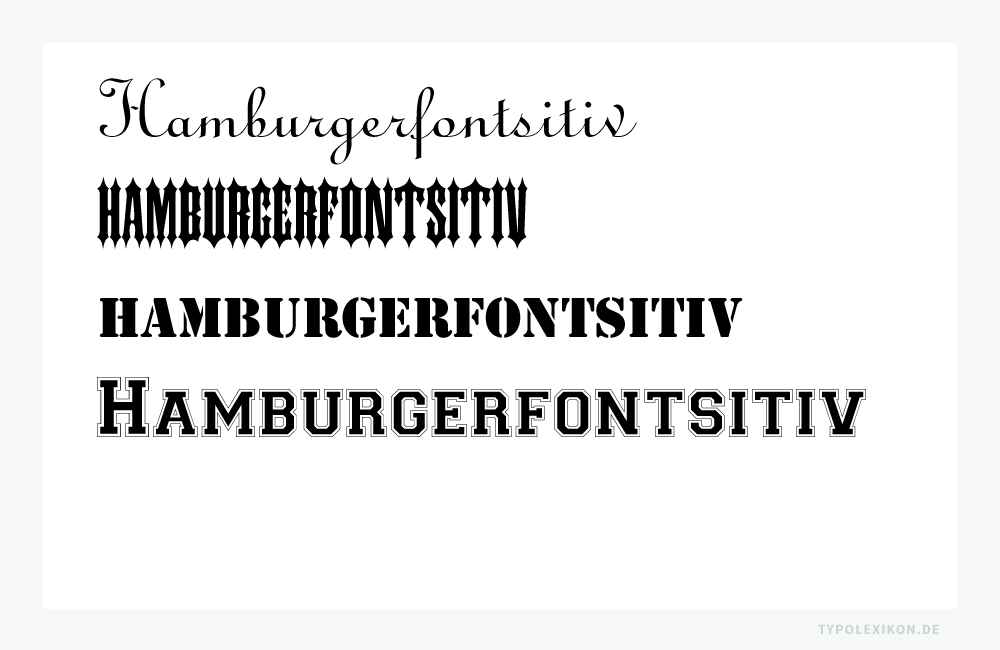
Heute werden bei den vielen Font Foundries u.a. auch Schreibschriften, Pinselschriften, Decorative und Designerschriften als »Display Typefaces« gelistet. 1) Display-Schriften gibt es in unterschiedlichen Schrifttechnologien, beispielsweise als OpenType Fonts, sowohl kostenpflichtig als auch kostenfrei.